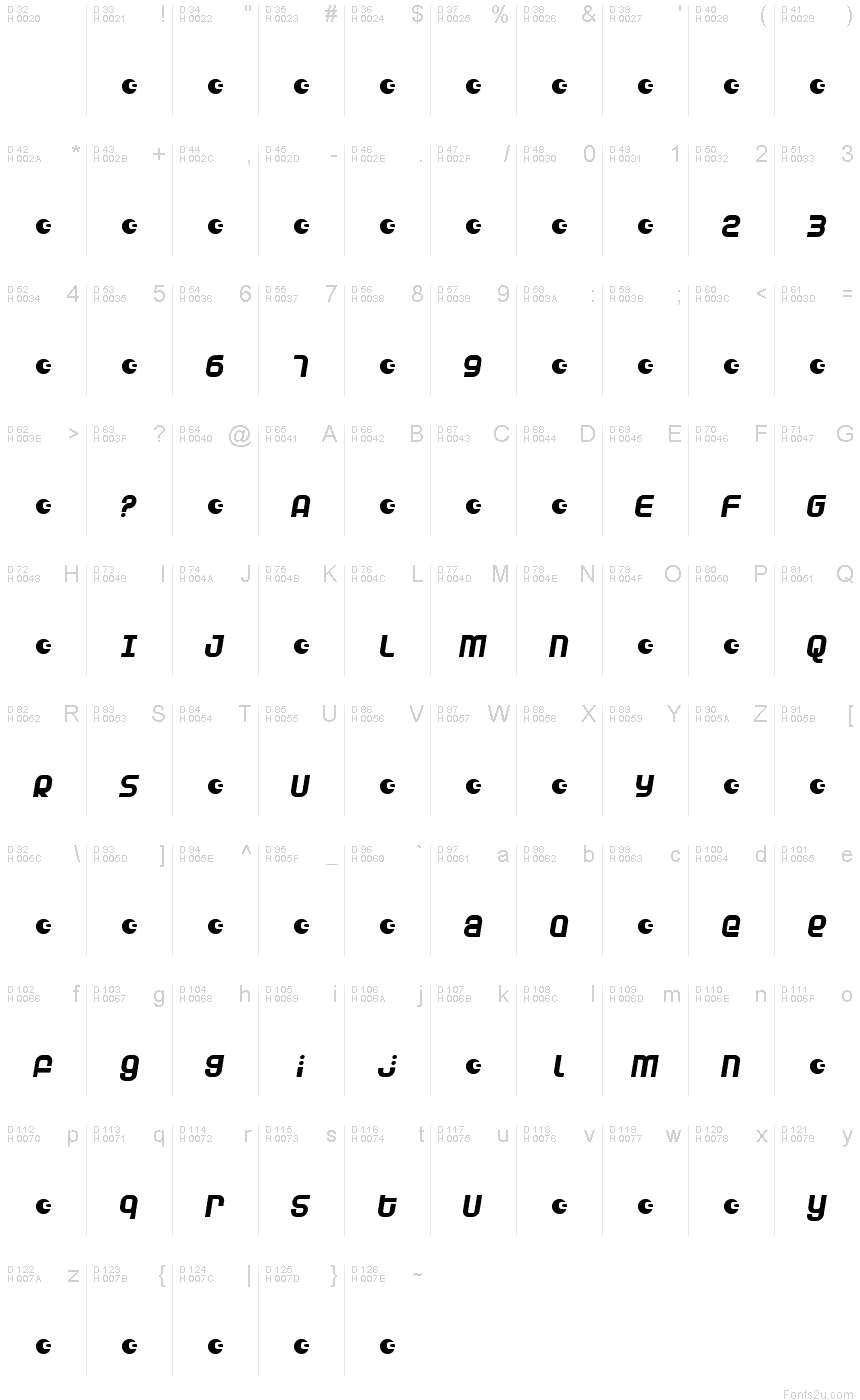
Dunebug Alternates 45MPH od Dunebug to nowoczesny, darmowy font typu display, który sprawia wrażenie, jakby był w ciągłym ruchu. Wysokie, zaokrąglone litery pochylają się do przodu, nadając im aerodynamiczny charakter, a masywne kreski i ścięte rogi dodają nagłówkom odważnego, sportowego pazura. Wyglądają jak numery startowe namalowane na asfalcie – są czyste, szybkie i nieco drapieżne.
Dzięki Dunebug Alternates 45MPH nadasz kineticznego vibe’u wydarzeniom wyścigowym, markom motoryzacyjnym, napojom energetycznym, plakatom sportów akcji, tytułom w grach czy bannerom konferencji technologicznych. Ten darmowy krój pisma błyszczy w dużych rozmiarach, gdzie jego opływowe kształty mogą w pełni wybrzmieć. Zestawiaj go z prostym, dyskretnym bezszeryfowym krojem w podpisach i tekście głównym, aby te szybkie formy pozostały w centrum uwagi.